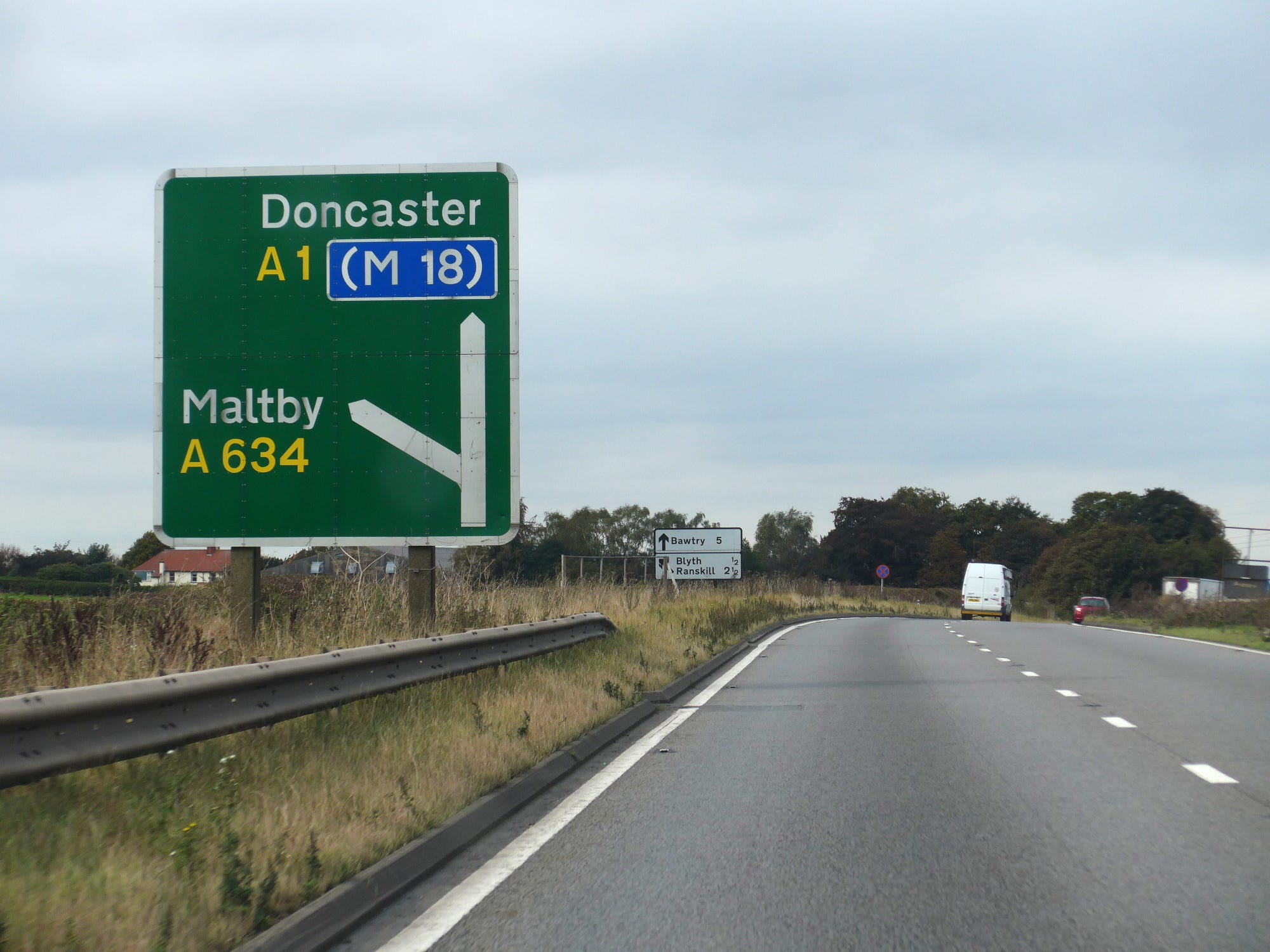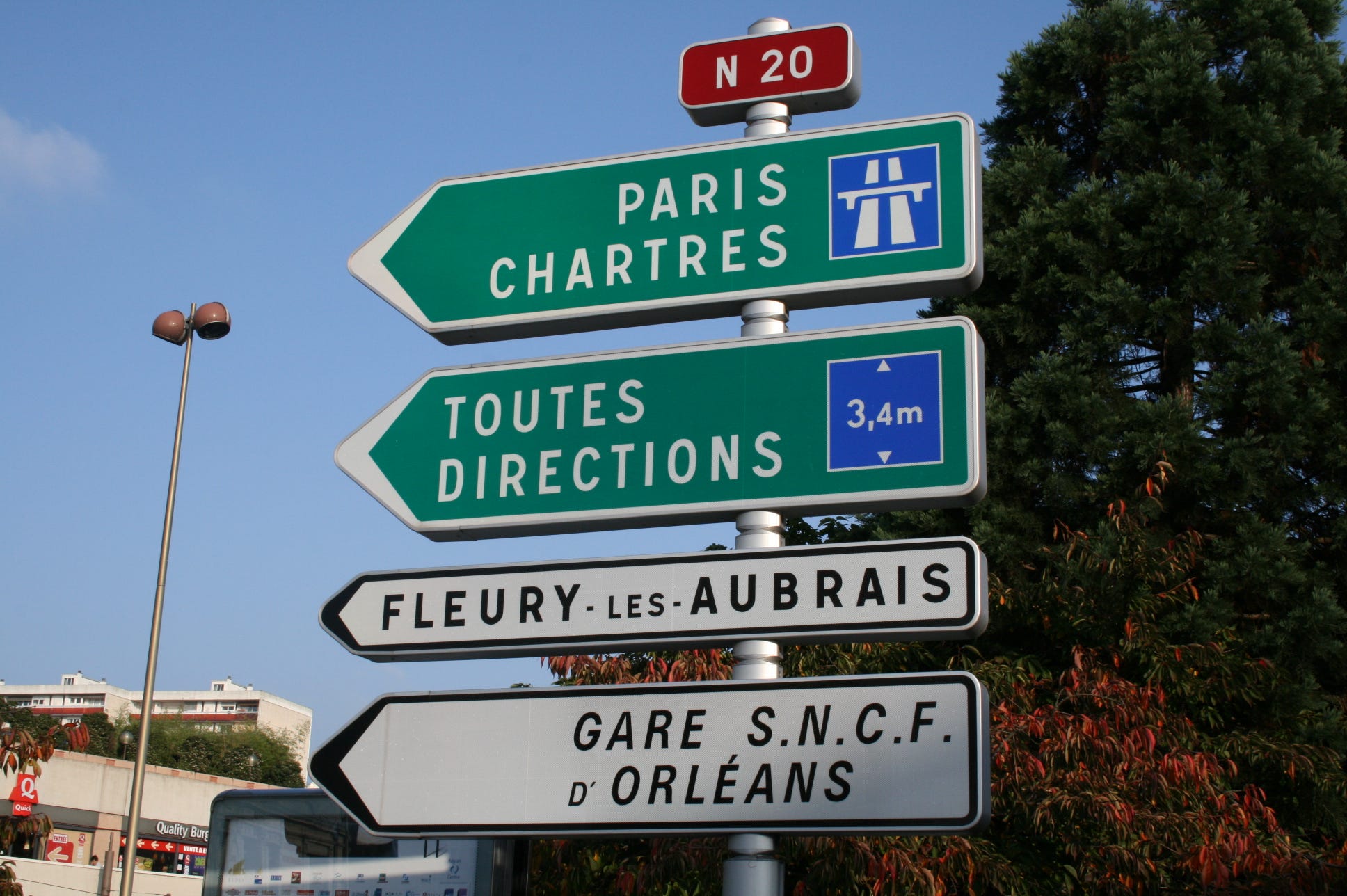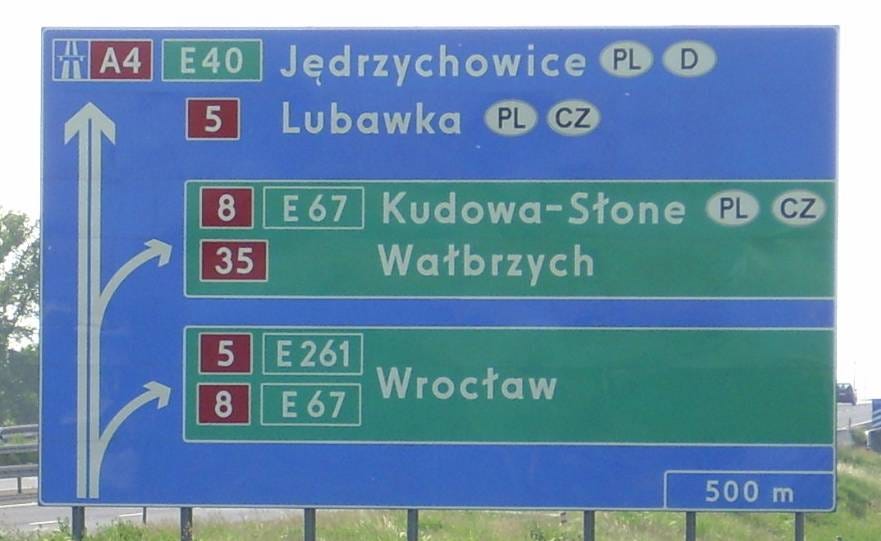
É pouco provável que o jesuíta belga Ferdinand Verbiest vislumbrasse os séculos por vir da mobilidade urbana enquanto, em 1672, construía o primeiro automóvel. Essa história, contudo, precisa de um pouco de cuidado com as palavras. O que chamamos de automóvel, neste caso, é um veículo de pouco mais de 60 cm movido por um propulsor a vapor, e que não carregava nada além desse mesmo propulsor. A palavra “carro” vem do latim carrus, que designa um veículo celta que carregava pessoas. Já o projeto de Verbiest malemá andava sozinho; não era carro, mas faz sentido a soma auto+móvel. Ainda nesse negócio de palavras, Verbiest usava o termo “motor” em seus diários, mas a engenharia moderna classifica o mecanismo dele, que usava vapor d’água para empurrar um disco coletor que tracionava as rodas traseiras e empurrava o carro automóvel para frente, como uma turbina.
O veículo do missionário e astrônomo flamengo precisa desses asteriscos para entrar na história do carro, mas era um sinal de que a humanidade ia querer colocar máquinas a vapor movidas a combustíveis fósseis em tudo que fosse possível. Centenas de anos depois, o fetiche pelo carro transformou a relação que temos com as cidades, fazendo com que novos centros urbanos privilegiassem o transporte automotivo desde sua concepção (deixemos o aspecto hostil disso para outro momento). Enquanto as fábricas cuspiam carros aos milhares, governos moveram mundos para criar estradas e rodovias que acomodassem milhares de automóveis, e também regulamentaram o transporte rodoviário padronizando vias e formatando a sinalização rodoviária. A história das tipografias utilizadas em rodovias e placas de trânsito, com suas criações, especificações e formas de uso, é o quilômetro zero desta edição do Tipo Aquilo.
Enquanto você lia esse lenga-lenga histórico, 146 carros novos foram vendidos mundo afora (ABI Research), 2,1 pessoas morreram e até 98 pessoas sofreram ferimentos em acidentes de trânsito (OMS). Placas de trânsito fazem parte de um contexto em que a tipografia pode (e deve) salvar vidas, facilitando o deslocamento de motoristas e orientando-os sobre quaisquer incidentes no trajeto. As tipografias mais comumente encontradas em estradas e rodovias de países com alfabeto latino foram desenvolvidas entre as décadas de 1920 e 1960 por times multidisciplinares compostos de engenheiros, psicólogos, pesquisadores e, em alguns casos, por designers.
Antes desses sistemas tipográficos, as placas tinham suas letras e setas abertas à mão, com pincel e stencil, sem nenhuma uniformidade entre países e até mesmo entre províncias e cidades. O Touring Club Italiano foi a primeira organização de motoristas a reivindicar por um sistema unificado de sinalização rodoviária, tendo produzido entre 1896 e 1974, mais de 700.000 placas de trânsito para municípios da Itália. Contudo, até pouco depois da Segunda Guerra Mundial, cada lado do Oceano Atlântico seguiu seu próprio caminho no desenvolvimento de seus sistemas de sinalização rodoviária. A Europa deu preferência à representação iconográfica, usando pictogramas para representar perigos, acidentes e pontos de atenção nas vias. Os Estados Unidos, por sua vez, optou por placas textuais, uniformizando a linguagem usada ao longo dos anos. Essa diferença é notável até os dias atuais, com países signatários da Convenção de Viena sobre Trânsito Viário de 1968 (que o Brasil é signatário desde 1981) adotando sinalização predominantemente iconográfica, enquanto EUA e Canadá usam placas com avisos textuais.
A Alemanha deu o primeiro passo na criação de uma tipografia para sinalização de trânsito, ao publicar a norma DIN 1451 (DIN é de Deutsches Institut für Normung, a ABNT alemã) com três alfabetos voltados para uso em desenhos técnicos, placas de trânsito, gravações em materiais industriais, entre outros propósitos. Um desses alfabetos, o Engschrift (escrita condensada), deriva de um modelo para formas de letras criado pela companhia prussiana de ferrovias em 1905, que tornou-se padrão com a unificação das ferroviárias teutônicas em 1920. A Engschrift já era bastante usada quando os engenheiros da DIN publicaram a norma 1451 institucionalizando a escrita condensada e trazendo outros dois modelos derivados dela: a Mittelschrift (escrita média) e Breitschrift (escrita larga). Atualmente, a DIN é usada em placas de trânsito não apenas na Alemanha, mas também em Cingapura, Chéquia, Letônia, Síria e nos países da Comunidade de Desenvolvimento da África Austral.
O Reino Unido, por sua vez, adotou uma tipografia própria para a reconstrução de seu sistema de rodovias, que havia sido destruída na Segunda Guerra Mundial. Os ingleses Jock Kinneir e Margaret Calvert foram os primeiros designers a trabalhar num sistema de sinalização rodoviária, tendo desenvolvido entre 1957 e 1963 especificações para a composição de placas de orientação. Kinneir e Calvert criaram também uma tipografia inspirada na Akzidenz Grotesk e nas letras criadas por Edward Johnston para o sistema de metrô de Londres, que gerou críticas de designers e artistas mais conservadores quando as primeiras letras foram publicadas no The Times em 1958. David Kindersley, escultor e gravador inglês, foi a principal voz entre os críticos, criando um coro favorável à sua tipografia serifada para as placas. Após uma bateria de testes encomendada pelo Ministério dos Transportes do Reino Unido, em 1962, a os tipos de Kinneir e Calvert foram mantidos, e atualmente encontram-se em uso também em outros países, como a Espanha, Portugal, Malta, Índia, Irã e Hong-Kong.
O sistema rodoviário francês também conta com caracteres próprios para composição de placas, usando majoritariamente os modelos L1 e L2 (com caracteres maiúsculos) para indicar cidades ou vilarejos, e o L4 (com caracteres itálicos maiúsculos e minúsculos, inspirados na Univers) para locais e pontos de interesse próximos. Instituído em 1963, ele é utilizado tanto na França quanto em países africanos francófonos, como a Argélia e a Tunísia. Entre as décadas de 1960 a 1990, os modelos L1 e L2 foram também utilizados no sistema rodoviário brasileiro, embora o Brasil nunca tenha instituído uma tipografia de referência para a confecção de placas. Esse vazio faz com que seja possível encontrar placas mais antigas usando os caracteres L1/L2 e placas mais recentes que utilizam duas tipografias utilizadas nas rodovias norte-americanas: a FHWA Series e a Clearview (imagens, logo no início da edição).
Os EUA teve uma história particular com a indústria automotiva e a regulamentação da sinalização rodoviária. Durante a primeira metade do séc. XX, houve uma gama de esforços dedicados a uniformizar placas e sinais entre os 51 estados, que espalharam os semáforos (inventados em 1912) e um sistema que indicava risco para o motorista de acordo com a quantidade de lados da placa. Placas redondas (com infinitos lados) indicavam risco máximo e eram reservadas para cruzamentos com ferrovias; placas octogonais indicavam pontos de parada obrigatória; e placas retangulares eram designadas para avisos textuais. Em 1948, a Federal Highway Administration publicou sua primeira especificação de formas de letras para sinalização rodoviária, composta de seis modelos indo das letras mais condensadas (A) até as mais largas (F), com variações de peso para contrastes positivo e negativo. A FHWA Series — posteriormente chamada de Highway Gothic — sofreu algumas revisões com o tempo, mas persiste até hoje como a tipografia padrão de sinalização rodoviária nos EUA.
Ao introduzir novos materiais fotorrefletores para placas de trânsito, as letras da FHWA Series passaram a sofrer com a formação de halos ao redor delas quando iluminadas pelos farois, e letras como “e”, “o” e “s” tornavam-se indistinguíveis. Com isso, uma nova especificação de letras foi desenvolvida com supervisão da FHWA, e em 2004, a instituição passou a recomendar uma nova tipografica, chamda Clearview, desenvolvida por Don Meeker e James Montalbano a pedido do Texas Transportation Institute, para composição de placas de sinalização rodoviária. Desde então, uma batalha foi erguida, com a mesma instituição retirando a recomendação em 2016, após estudos não comprovarem uma legilidade superior da Clearview e até apontarem problemas com seu uso em contraste negativo (texto escuro em fundo branco). A recomendação foi reinstituída por lei em 2018, mas o uso da Highway Gothic ainda é predominante. Em províncias canadenses como Ontario e British Columbia, além de países como Indonésia e Filipinas, a Clearview ainda é recomendada.
Mas Cadu, afinal de contas, o que faz uma fonte ser considerada apropriada para sinalização rodoviária? Teoricamente, uma tipografia para sinalização rodoviária tem como algumas de suas características principais:
distinções mais evidentes entre letras parecidas, como “I”, “l” e “1”;
formas que funcionam melhor sob efeito de iluminação direta e halação (quando forma-se um halo luminoso ao redor das letras);
letras minúsculas com medidas de altura-de-x maiores, quando comparadas com fontes para texto;